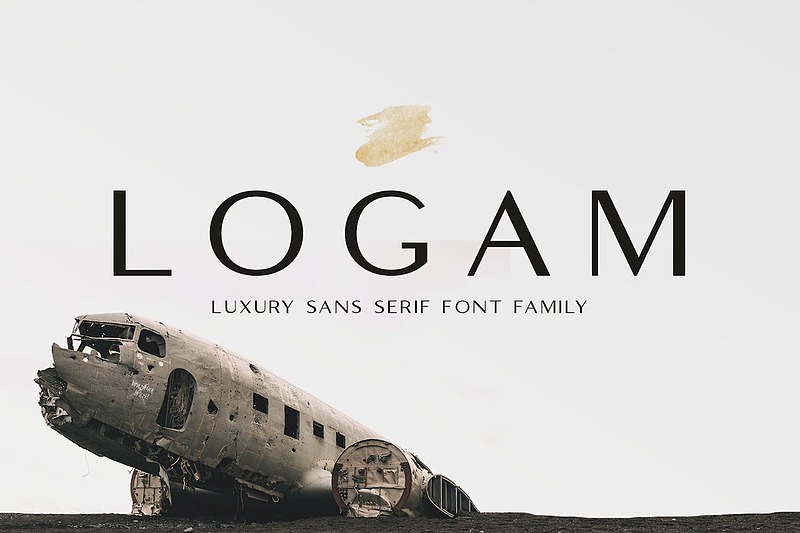
لوگام، یک خانواده فونت سنس سریف مدرن و لوکس است که دیزاین آن ما را به سبک مینیمال مدرن ارجاع میدهد. ویژگیهای متمایز لوگام کنتراست نسبتاً کم استروکها، شیپ و ساختار کاراکترها کمی متمایل به گرد است و تأکید مؤکدی بر بیزینس و سیمپلیسیتی دارد.
لوگام دارای یک مجموعه سبک یا استایلیستیک ست اورجینال است که وقتی روشن شود، ویژگیهای تایپیکال پوینتدپِن را به برخی از کاراکترهای کوچک اضافه میکند. علاوه بر این، لوگام دارای کپیتالهای کوچک برای زبان لاتین و همچنین چندین لیگچر جالب است.
لوگام، از ابتدا با منطق ساختاری خاص خود ساخته شده است: تلفیقی از هندسه خالص و تعادل اپتیکال. با ترکیب انواع سبک، لوگام برای لوگو، کارت تبریک، نقلقول، پوستر، برندسازی، نِیمکارت، استیشنری، طراحی عنوان، سربرگ وبلاگ، پستهای شبکههای اجتماعی و تایپوگرافی مناسب است.
لوگام، همچنین برای آرت و ایلوستریشن، حروف پاکتنامه مدرن یا طراحی کتاب، سبک اتفاقی یا هپنینگ استایل مانند طراحی هنددراون یا طرح آبرنگ، طراحی هندکرافت، هر پروژه خودت انجامش بده، عنوان کتاب، فونت عروسی، طراحی پاپ وینتیج، یا هر قصد و نظری که پروژه هنری یا طراحی را زیبا و مد روز و ترند به نظر می رساند.
همه کاراکترهای کپیتال
در دوسبک رگولار و ایتالیک
لیگچرهای استاندارد
اعداد و علائم نگارشی (استاندارد اپن تایپ)
اکسنتها (نویسههای چندزبانه)
کاراکترهای چندزبانه: AÀÁÂÃÄÅCÇDÐEÈÉÊËIÌÍÎÏNÑOØÒÓÔÕÖUÙÜÚÛWYÝŸỲŸÆŒßÞþþ
طبقهبندی: سنس سریف
فاصلهگذاری: نرمال
اندازه بهینه: هر اندازهای